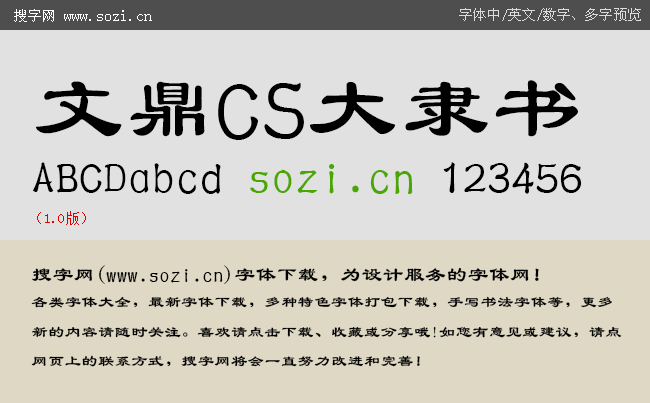
文鼎CS大隸書簡(jiǎn)
搜字網(wǎng)提供一款文鼎CS大隸書簡(jiǎn)中文字體下載,文鼎CS大隸書簡(jiǎn)是一款由文鼎字庫(kù)推出的隸書字體,文鼎CS大隸書略微寬扁,橫畫長(zhǎng)而直畫短,字體輪廓清淅,適合應(yīng)用于廣告設(shè)計(jì)、名片設(shè)計(jì)、包裝印刷、兒童產(chǎn)品設(shè)計(jì)等應(yīng)用。